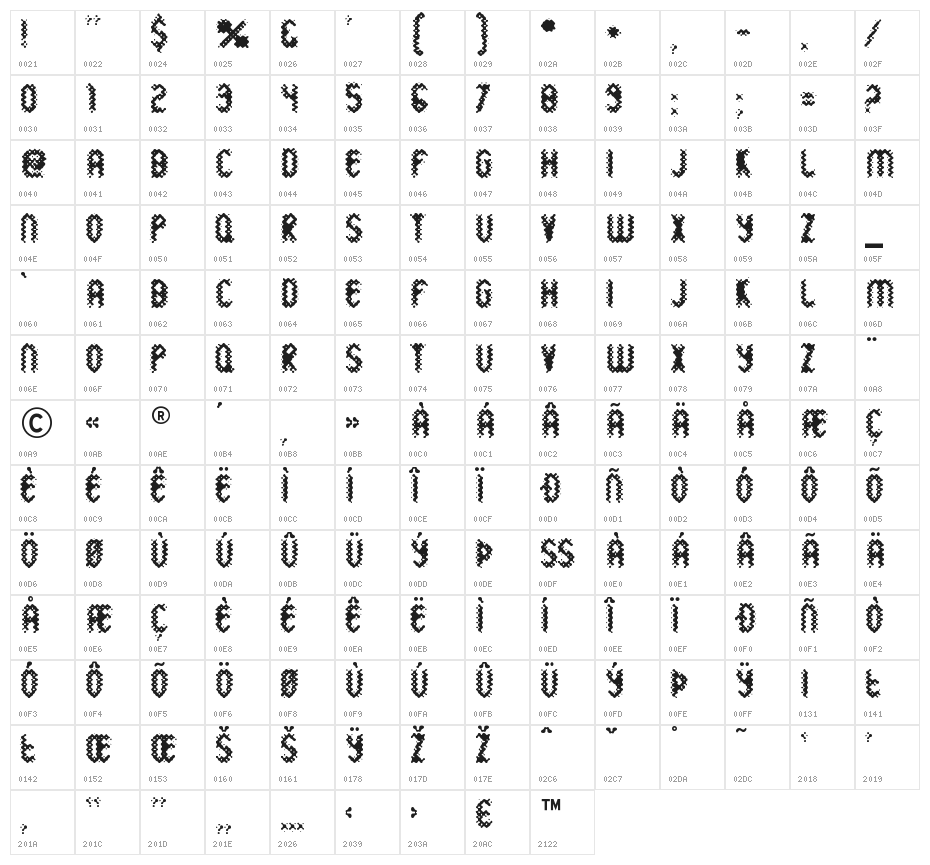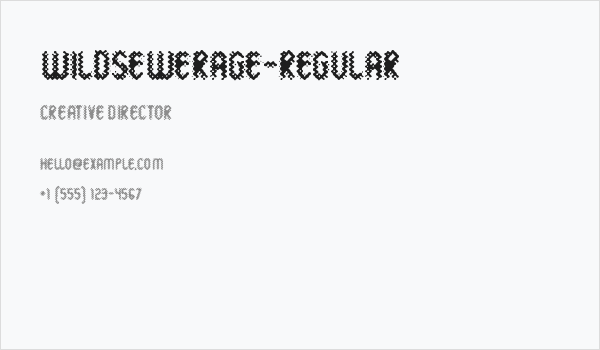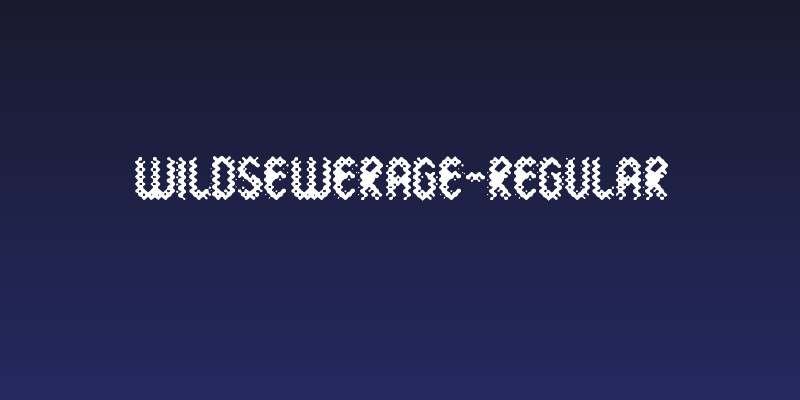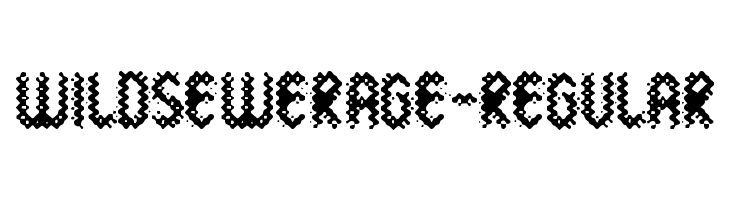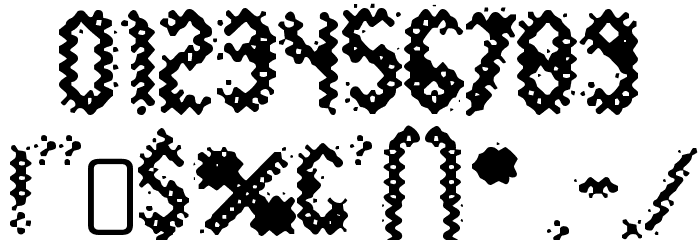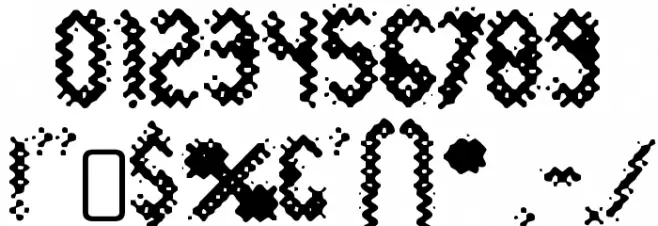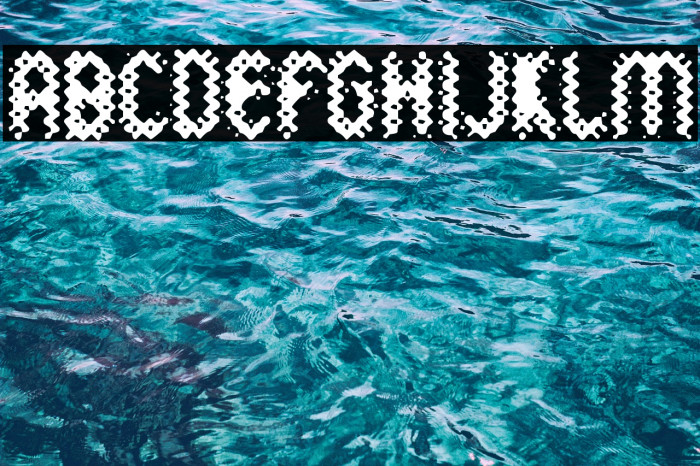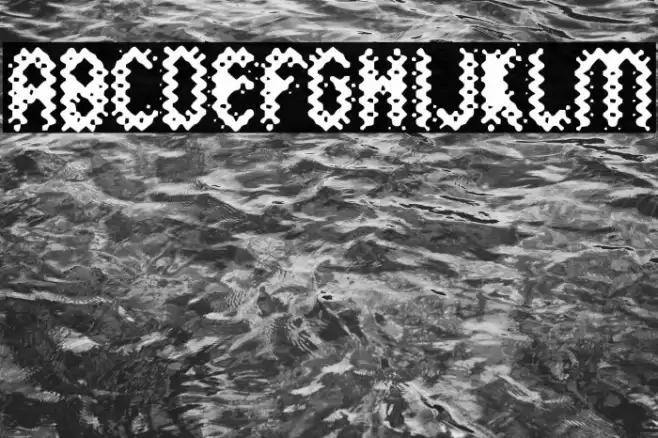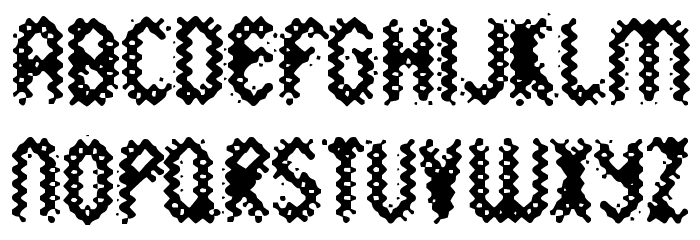
WildSewerage-Regular Font
✎ Distorted Eroded
| Caso de uso | Logos, Posters, Digital Art |
| Projetos propostos | Ideal for video game graphics, digital art projects, posters, and any design requiring a bold, unconventional typeface. |